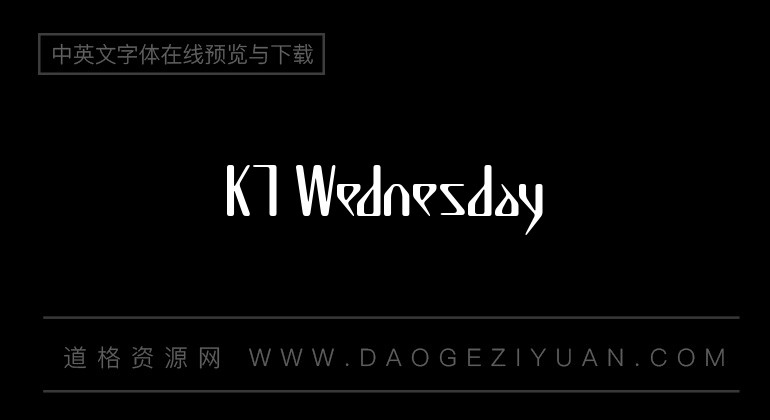
K7 Wednesday
K7 Wednesday 是一款由荷兰设计师 Karel Martens 设计的字体,它具有简洁而又有趣的外观,可以让您的设计看起来更加精致。K7 Wednesday 的字体特点是它的精细细节,它具有圆润的字形,并且能够提供色彩丰富的文本效果。它是一款完美的字体,既适合用于印刷,也可以用于网页设计。
K7 Wednesday是一款非常不错的手写艺术字体,具有很好的视觉感,适合于文化类的宣传设计、商业类品牌的广告和产品包装设计以及个性化文字排版等较多场景。